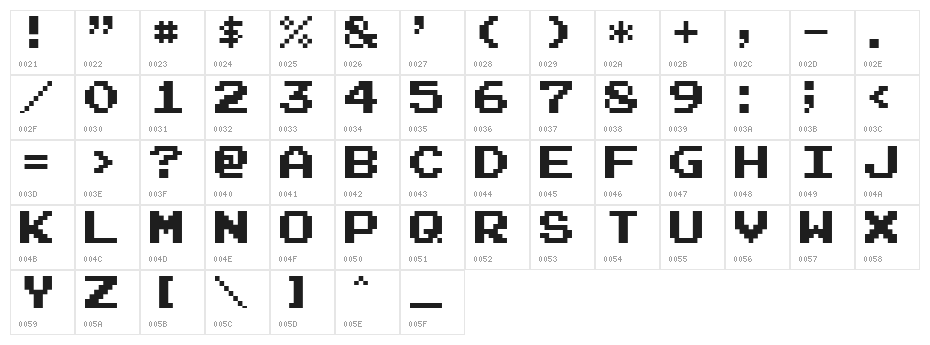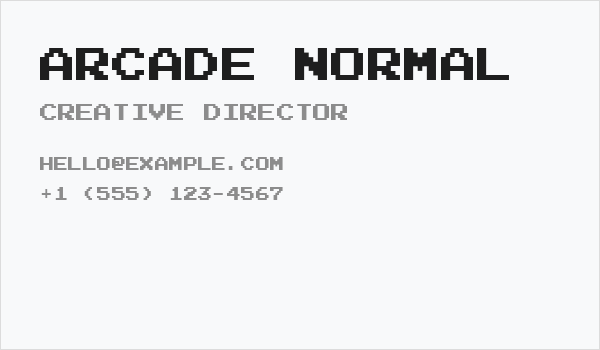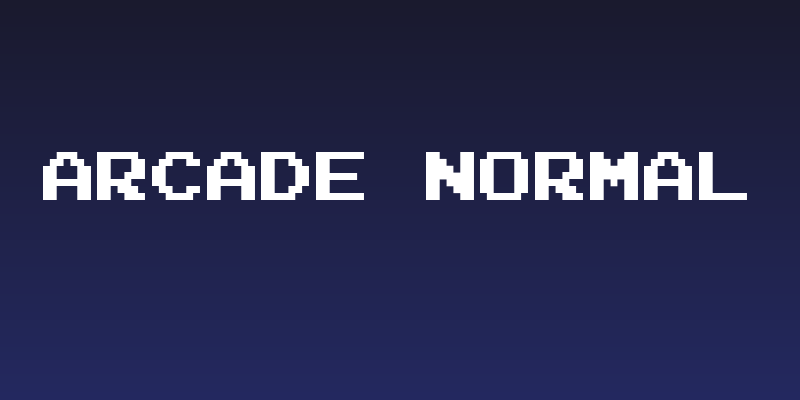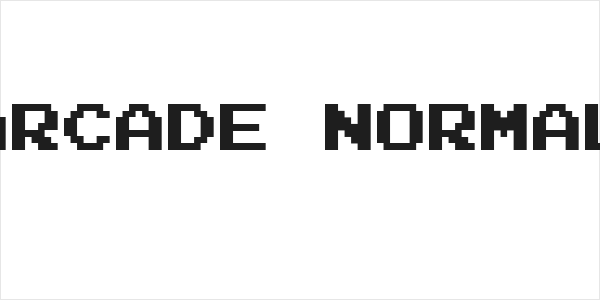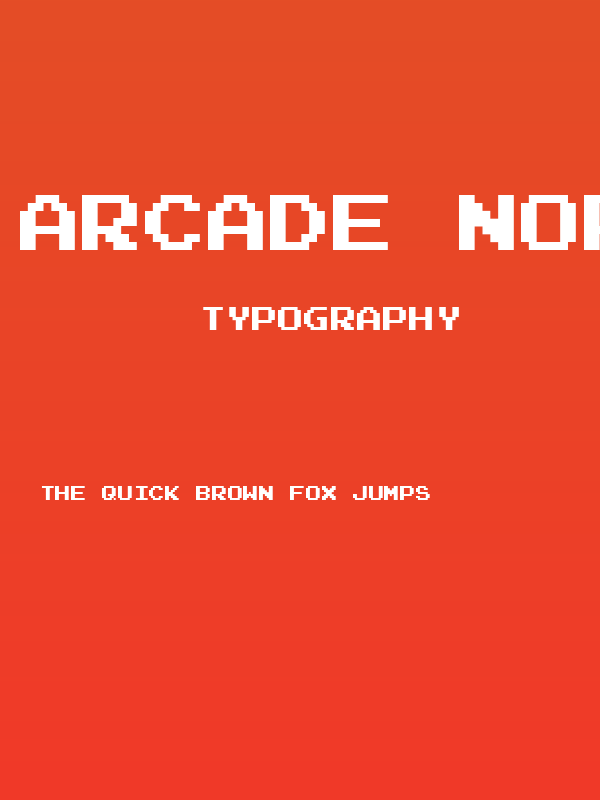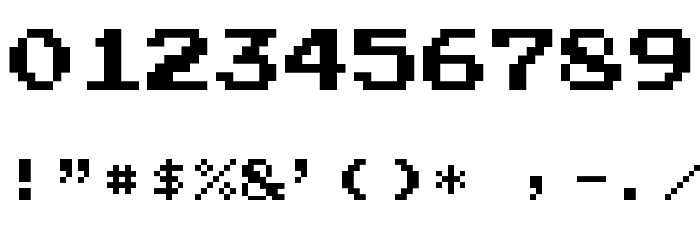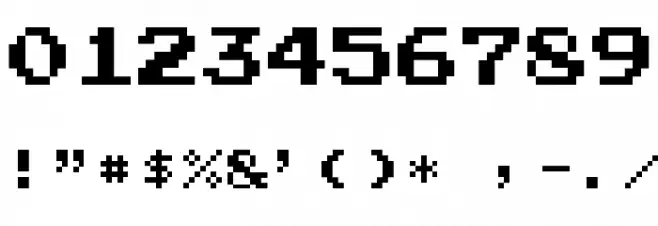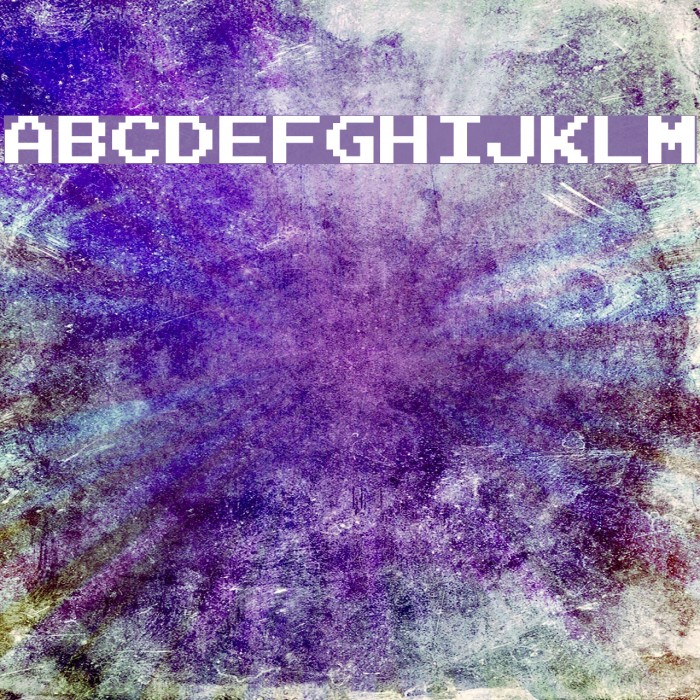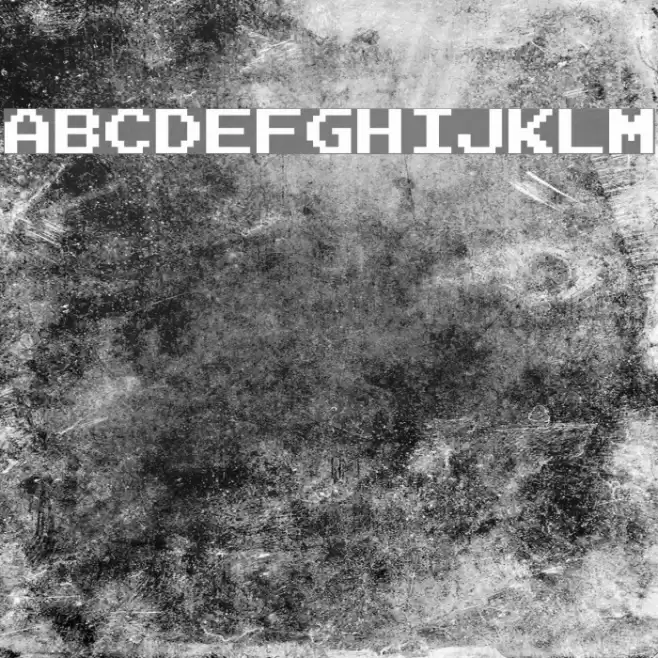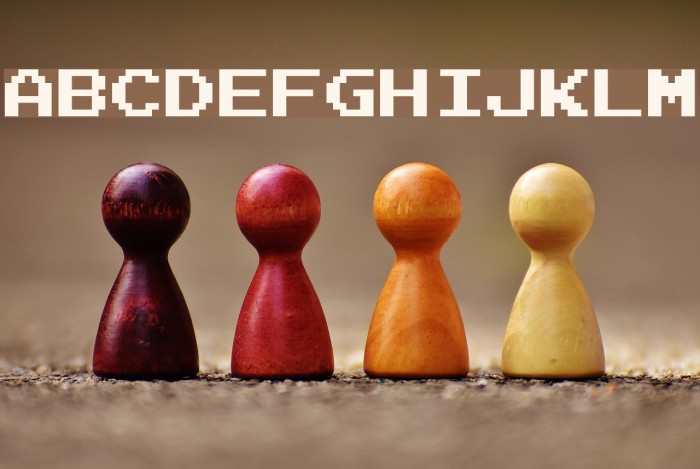
Arcade Normal Font
✎ Pixel
| Категория | Pixel |
| Межсимвольный интервал | Normal |
| Общий стиль | Vintage |
| Область применения | Headlines, Logos, Digital Art |
| Рекомендуемые проекты | Ideal for retro video game designs, nostalgic posters, themed event invitations, and digital art projects. |
| фиксируется шаг | Yes |